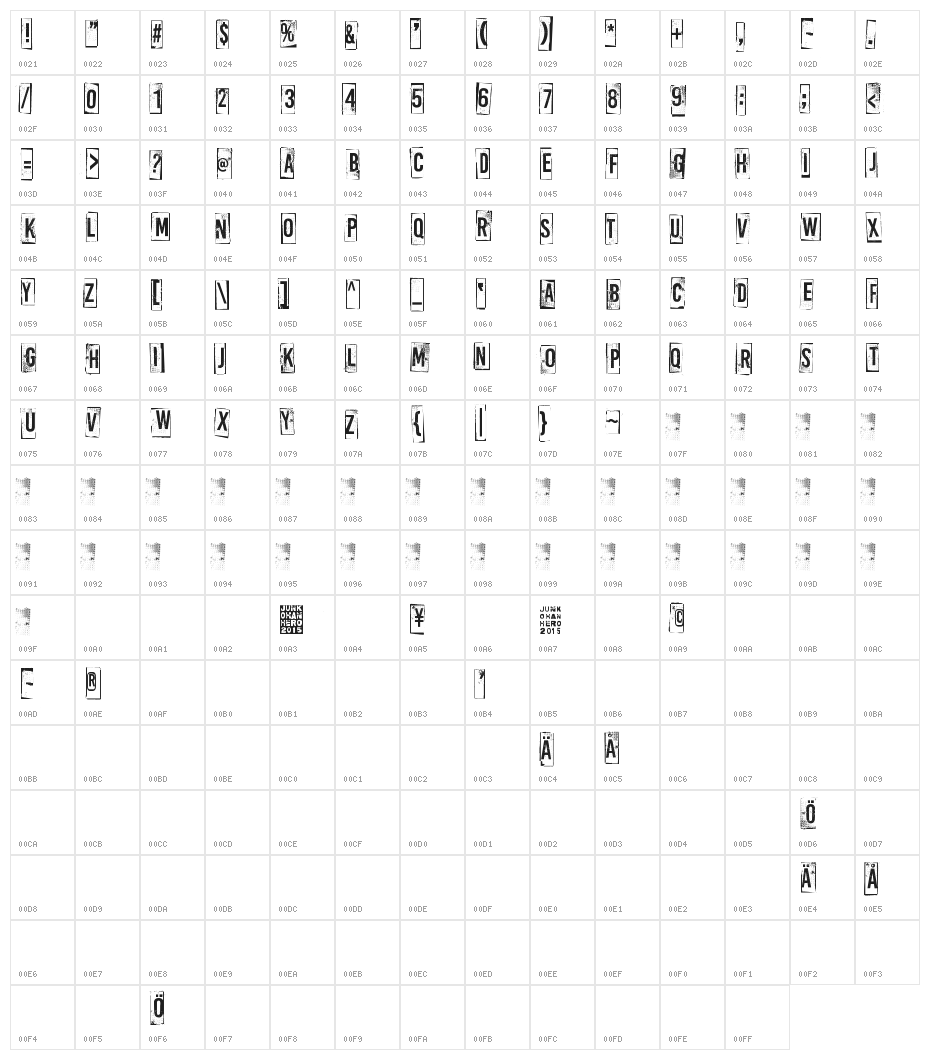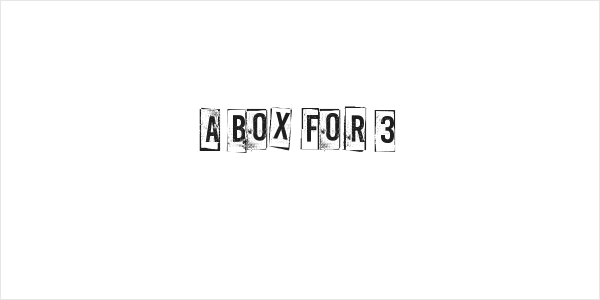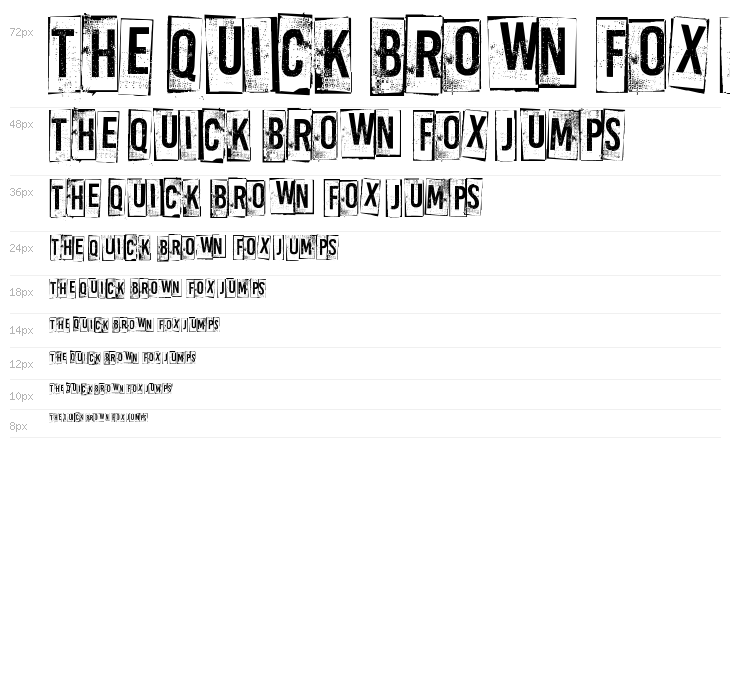
A Box For 3 Font
✎ Distorted Eroded
| Gesamtstil | Vintage |
| Vorgeschlagene Projekte | Ideal for posters, album covers, branding for vintage-themed products, or any design needing a rugged, industrial vibe. |